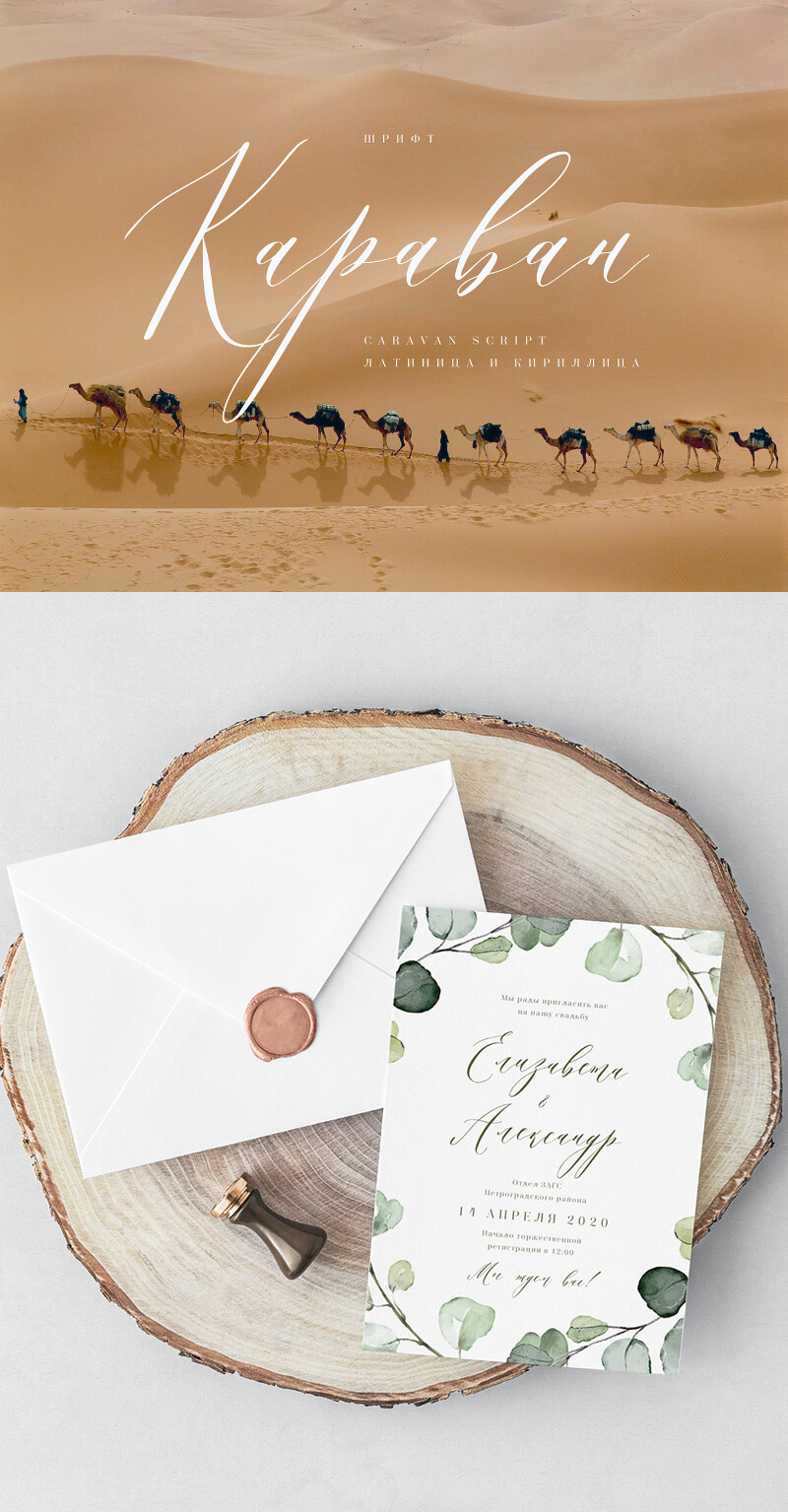
Шрифт - Караван
Караван - элегантный контрастный рукописный шрифт, вдохновлённый современной каллиграфией. Включает кириллическую и латинскую версии.